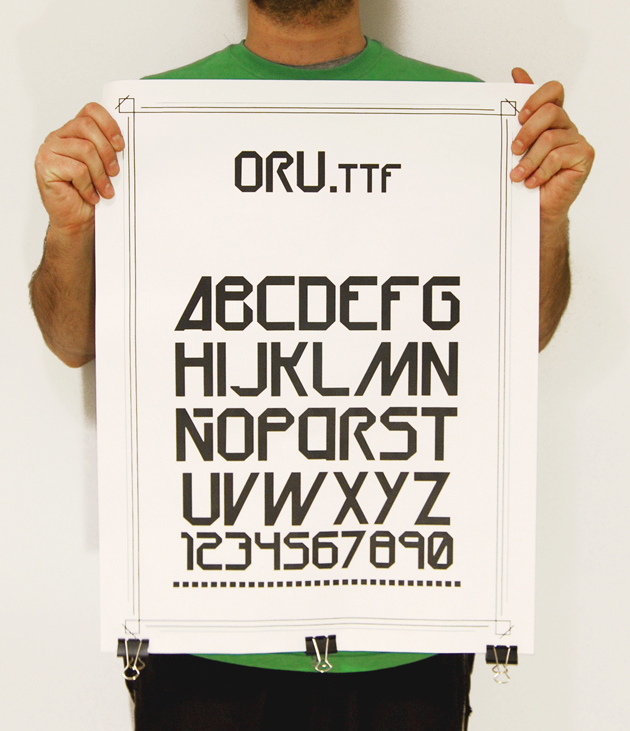
ORU ist eine kostenlose, kantige Techno-Display-Schrift aus breiten, starren Strichen und scharf abgeschnittenen Ecken. Ihre strenge Geometrie erinnert an Beschriftungen, die für Spielautomaten oder industrielle Bedienfelder geschnitten wurden.
Spielegrafiken und Veranstaltungsschilder sind völlig unterschiedliche Anwendungsbereiche, doch beide können ihre kompakten, mechanischen Formen nutzen, um Geschwindigkeit, Wettbewerb und Maschinerie zu signalisieren. Derselbe Aufbau eignet sich auch für Artwork und Merchandise im Bereich der elektronischen Musik, besonders wenn die Buchstaben an harte Logos, Paneele oder Rennsport-Grafiken erinnern sollen. In diesen Kontexten werden die Buchstaben eher zu Teil einer fiktiven Maschinenschnittstelle oder eines Streckenlogos, anstatt als neutraler Satz zu dienen.